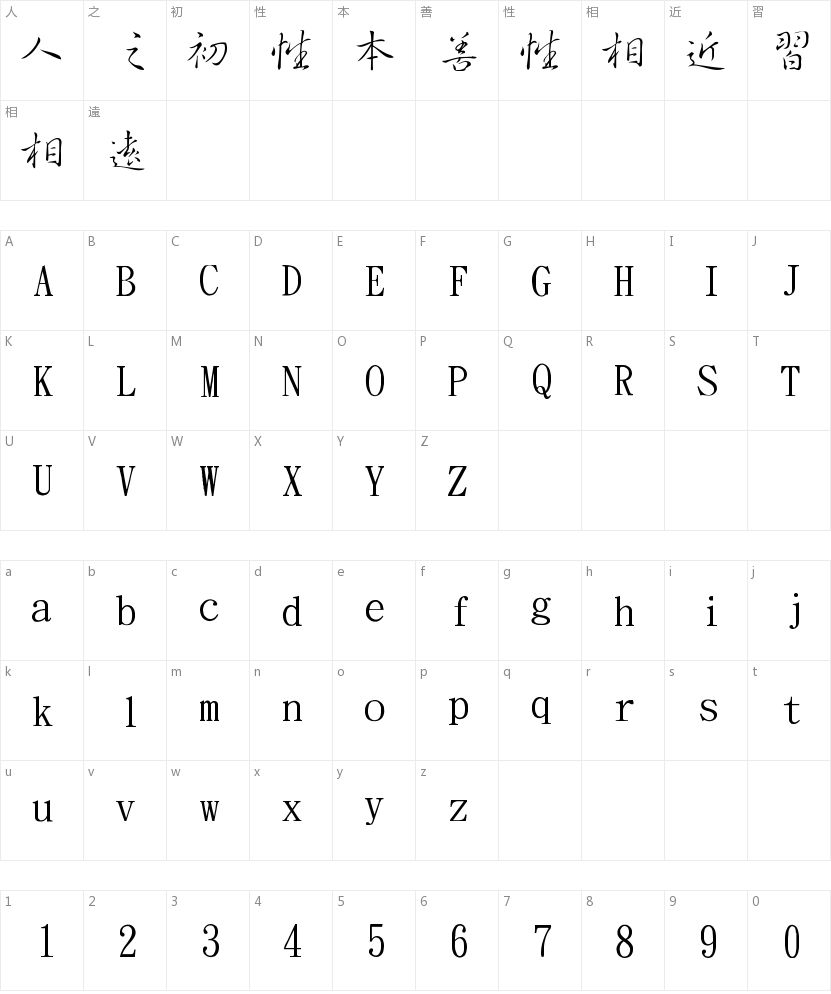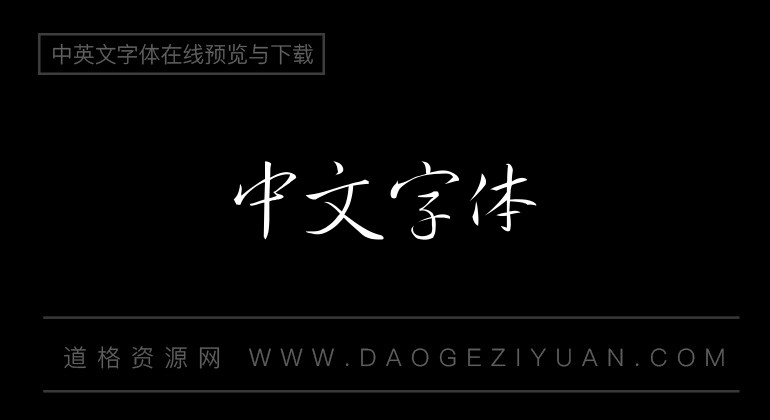
金梅新中行国际码
金梅新中行国际码字体是一种结合了中国传统文化特征与西方设计理念的现代汉字字体,由金梅新中行设计团队开发。它采用现代技术,结合中国传统文化特征,让汉字更加清晰、美观、大方。金梅新中行国际码字体以简洁大方的外形,展现出中国传统文化的韵味,可以用于多种应用场景,如报纸、杂志、网站、软件等,是一款非常适合中文使用的字体。
金梅新中行国际码是一款非常不错的手写艺术字体,具有很好的视觉感,适合于文化类的宣传设计、商业类品牌的广告和产品包装设计以及个性化文字排版等较多场景。
金梅新中行国际码字符映射图